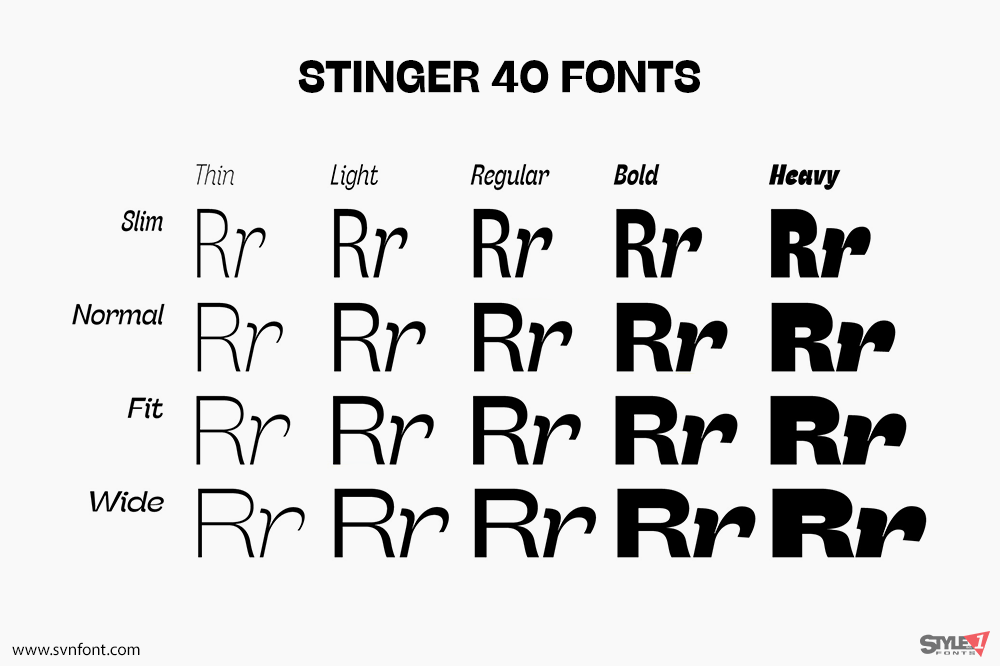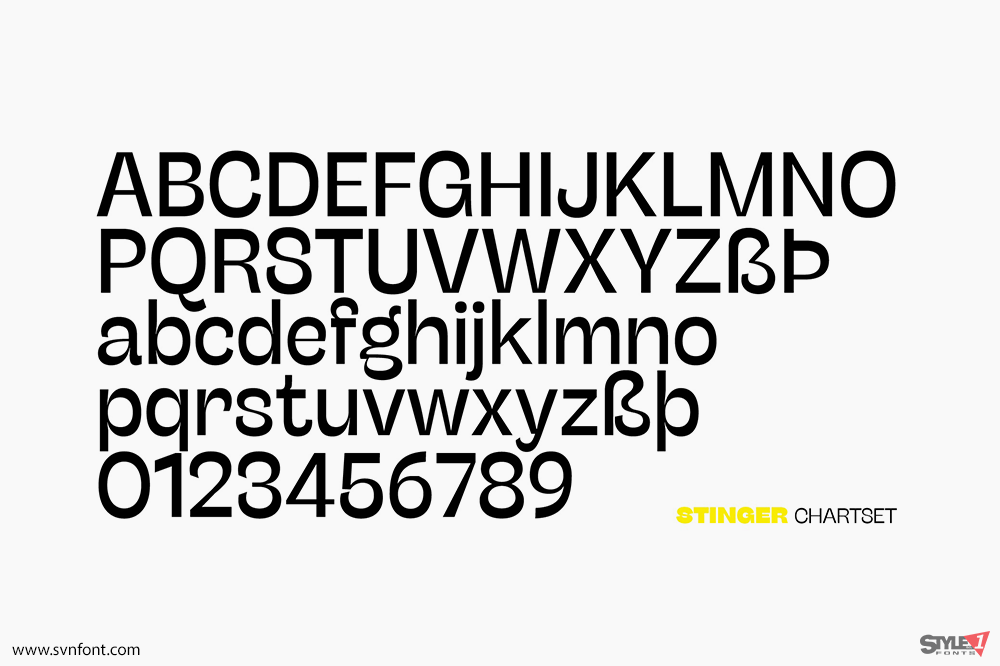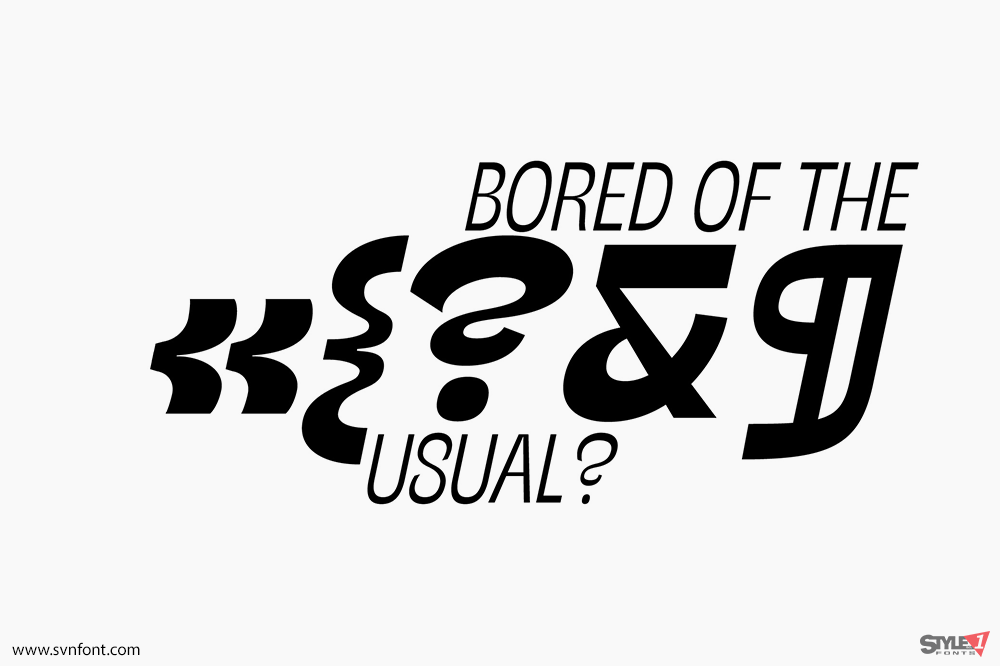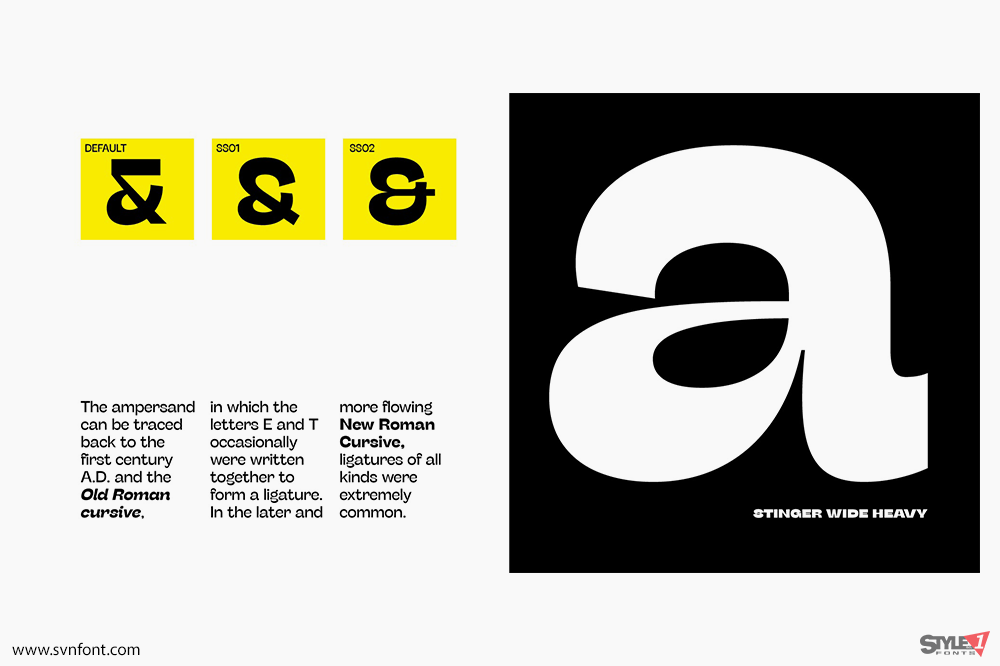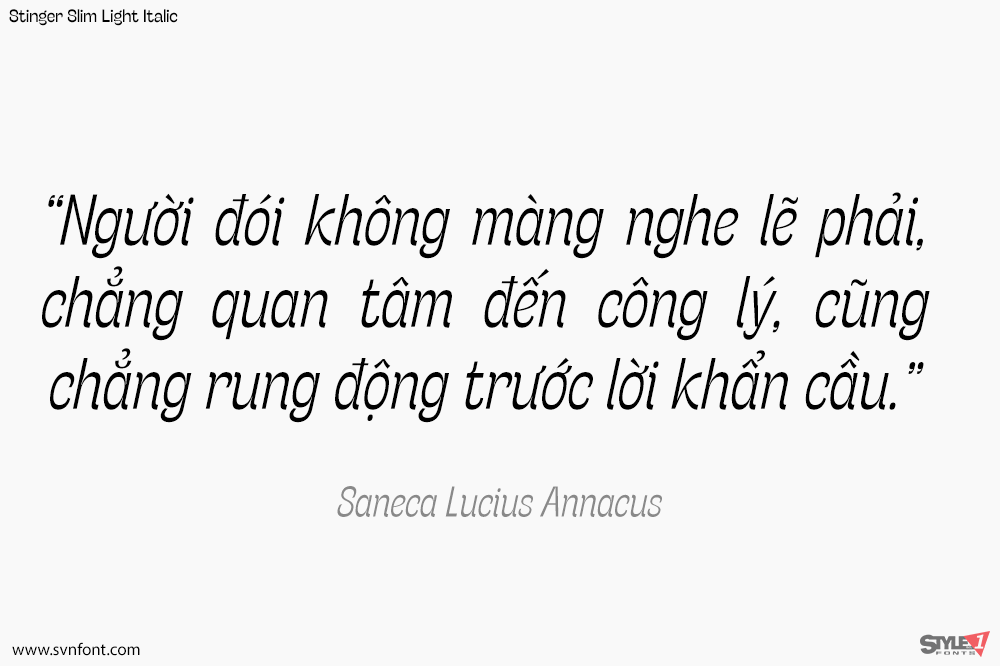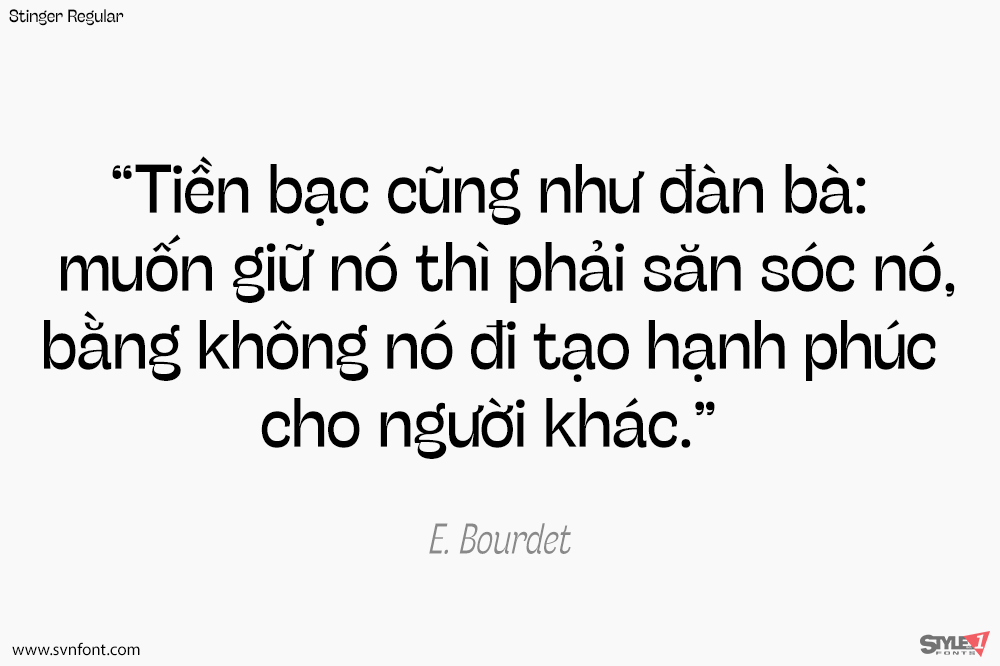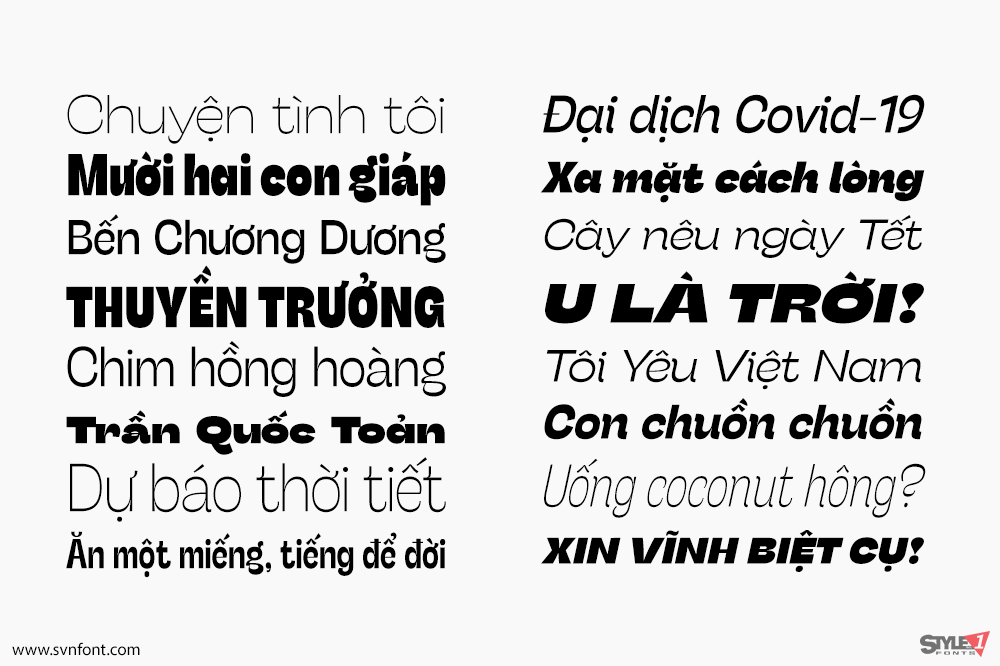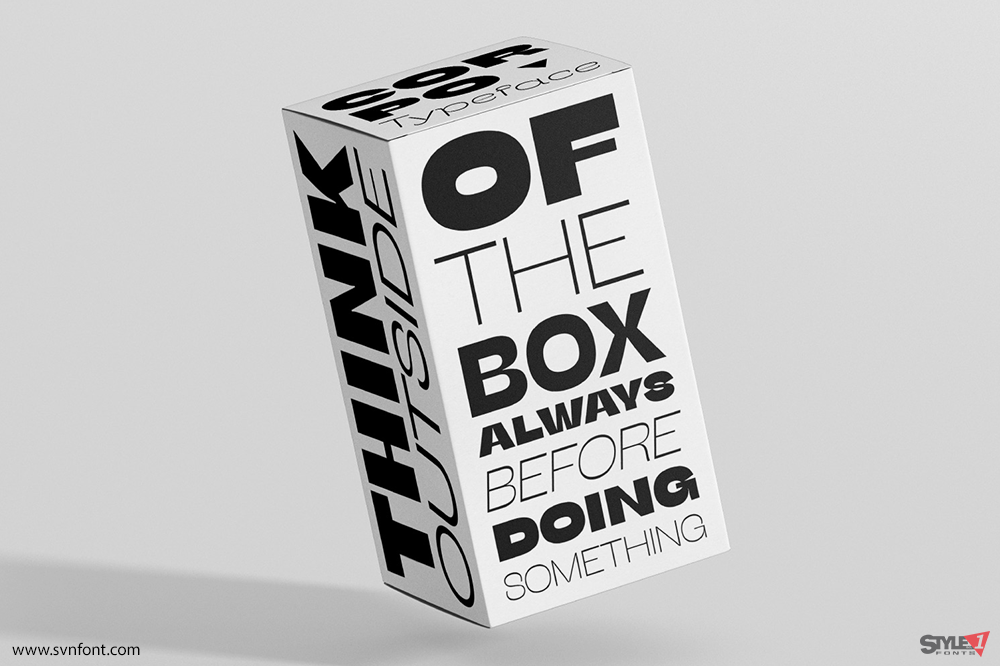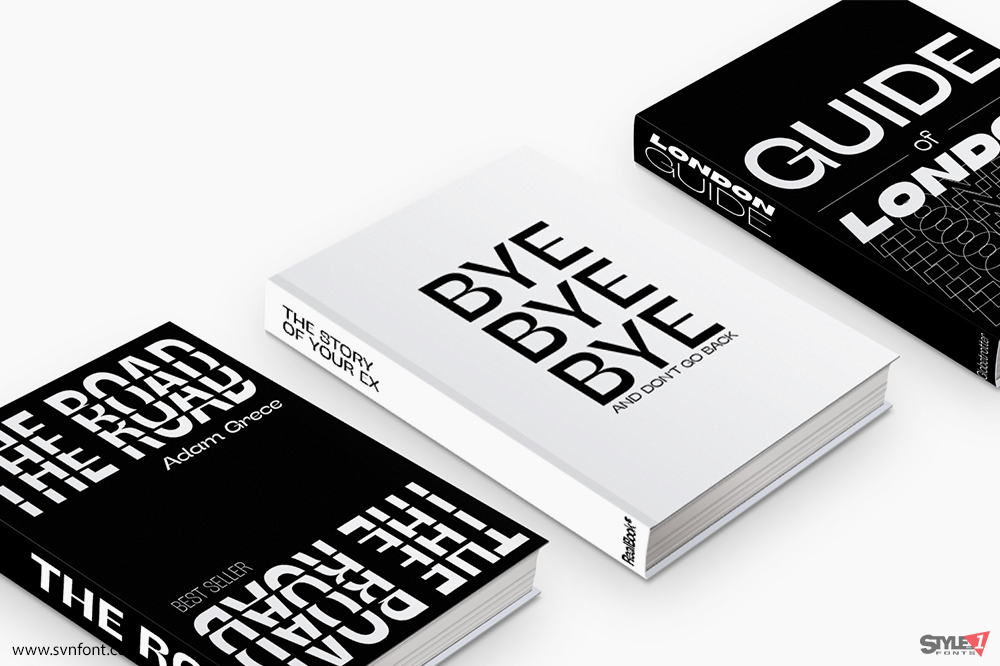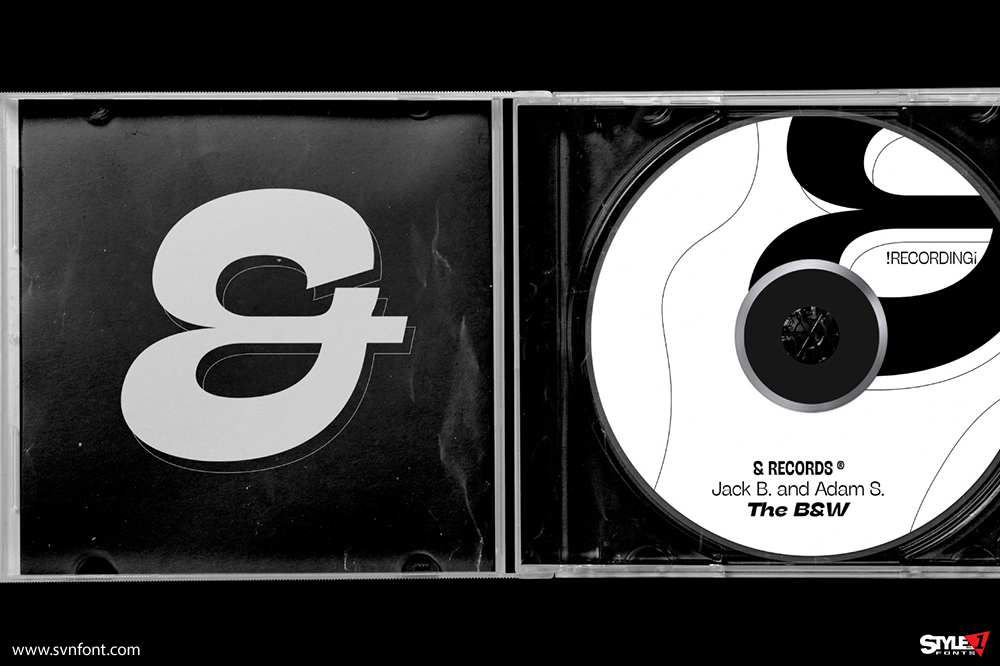
Stinger là một “siêu họ phông chữ” (super-family) được Zetafonts phát triển dựa trên cảm hứng từ phong cách tương phản ngược (reverse-contrast) đầy phá cách của thế kỷ 19. Thay vì đi theo sự hoàn hảo hình học của các phông Grotesque hiện đại, Stinger tạo dấu ấn riêng với:
- Cấu trúc đa dạng: Kết hợp giữa nét thư pháp thanh mảnh ở các biến thể thin và phong cách điêu khắc mạnh mẽ ở các biến thể heavy.
- Hệ thống đồ sộ: Gồm 40 phông chữ với 4 độ rộng (Normal, Fit, Wide, Slim) và 5 độ đậm khác nhau, đi kèm các bản Italic chuẩn.
- Công nghệ hiện đại: Hỗ trợ hơn 200 ngôn ngữ (Latinh, Cyrillic), tích hợp tính năng OpenType và phiên bản Variable Font giúp tùy chỉnh linh hoạt dải biểu cảm của chữ.
Nhờ sự kết hợp giữa tính thẩm mỹ “quái chiêu” và tư duy đa dụng của Sans Serif, Stinger đáp ứng mọi nhu cầu thiết kế:
- Hiển thị & Quảng cáo: Độ rộng Wide và các nét đậm cực kỳ phù hợp cho tiêu đề, poster hoặc thiết kế logo cần sự táo bạo, bắt mắt.
- Nội dung & Văn bản: Các bản Normal và Fit tối ưu hóa khả năng đọc; trong khi bản Slim là giải pháp hoàn hảo cho các không gian hẹp hoặc văn bản dài.
Stinger không chỉ là một công cụ sắp chữ mà còn là một tuyên ngôn về cá tính trong thiết kế đồ họa đương đại.
Nhà thiết kế: Francesco Canovaro, Cosimo Pancini, Andrea Tartarelli, Maria Chiara Fantini
Nhà phát hành: Zetafonts